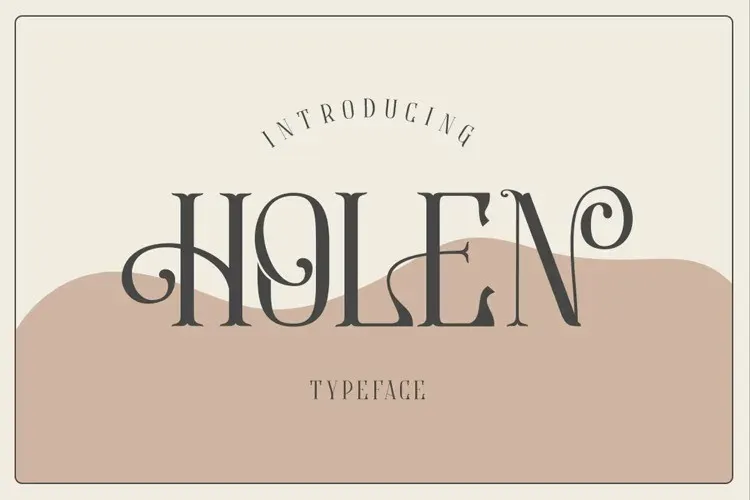
Holen Font – Fonte Grátis
Holen Font
A Holen Font é uma elegante tipografia serifada para uso no estilo display criada por Alit Suarnegara, com vários traços alternativos e suporte a múltiplas línguas. Seus detalhes geométricos são sutis, proporcionando curvas únicas e encantadoras que fluem naturalmente. Esta fonte é fácil de aplicar em qualquer projeto design, especialmente aqueles focados em conceitos elegantes e suaves, além de ser facilmente utilizada tanto no design quanto nos programas não-design, pois todos os alternativos e traços estão compatíveis com Unicode (PUA). Sua sofisticação e delicadeza tornam a Holen Font uma escolha perfeita para quem busca expressar elegância em seus projetos.